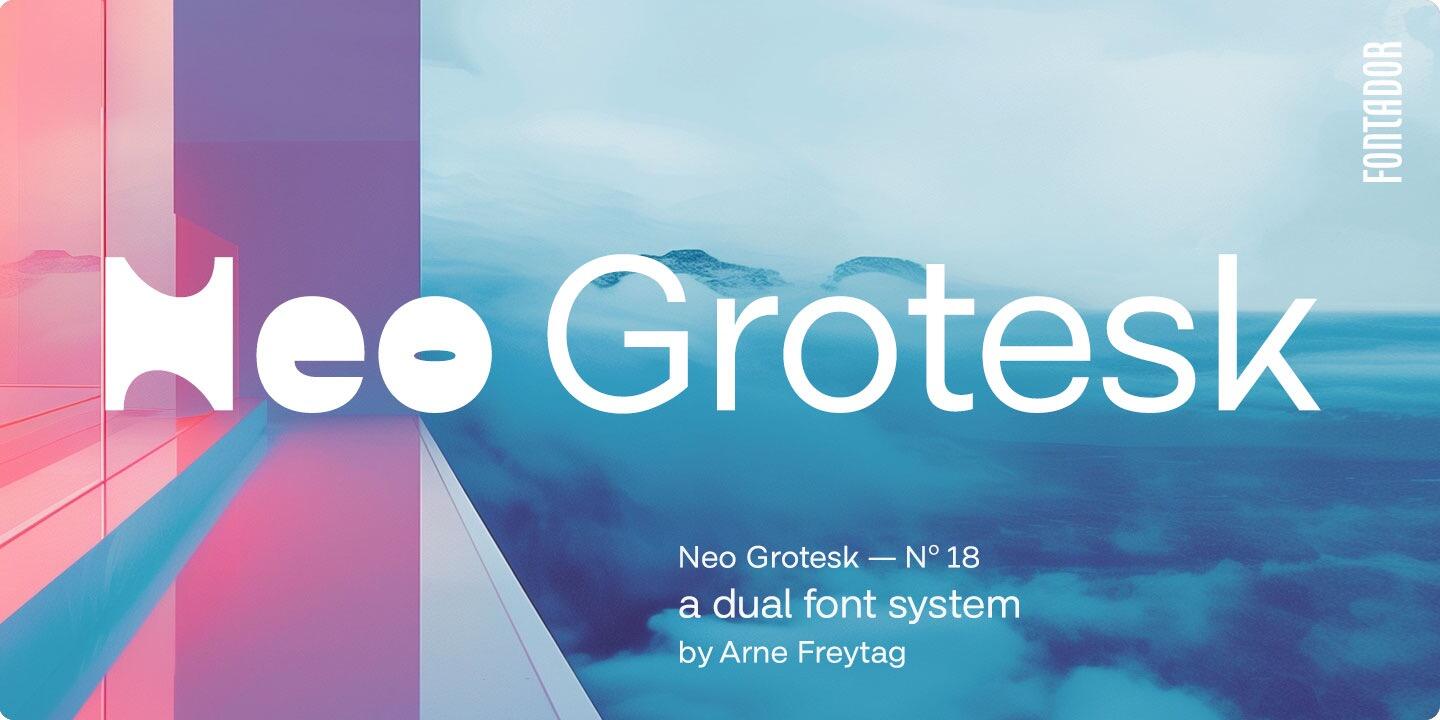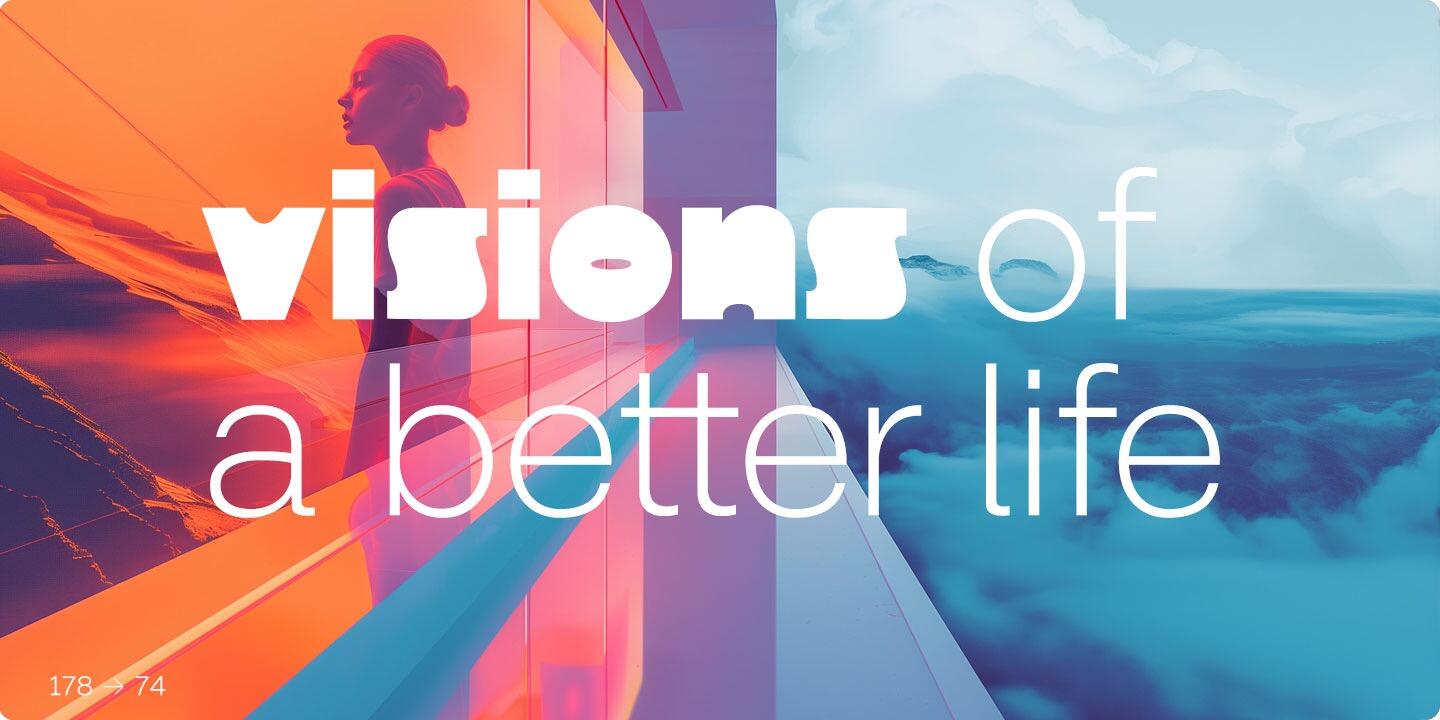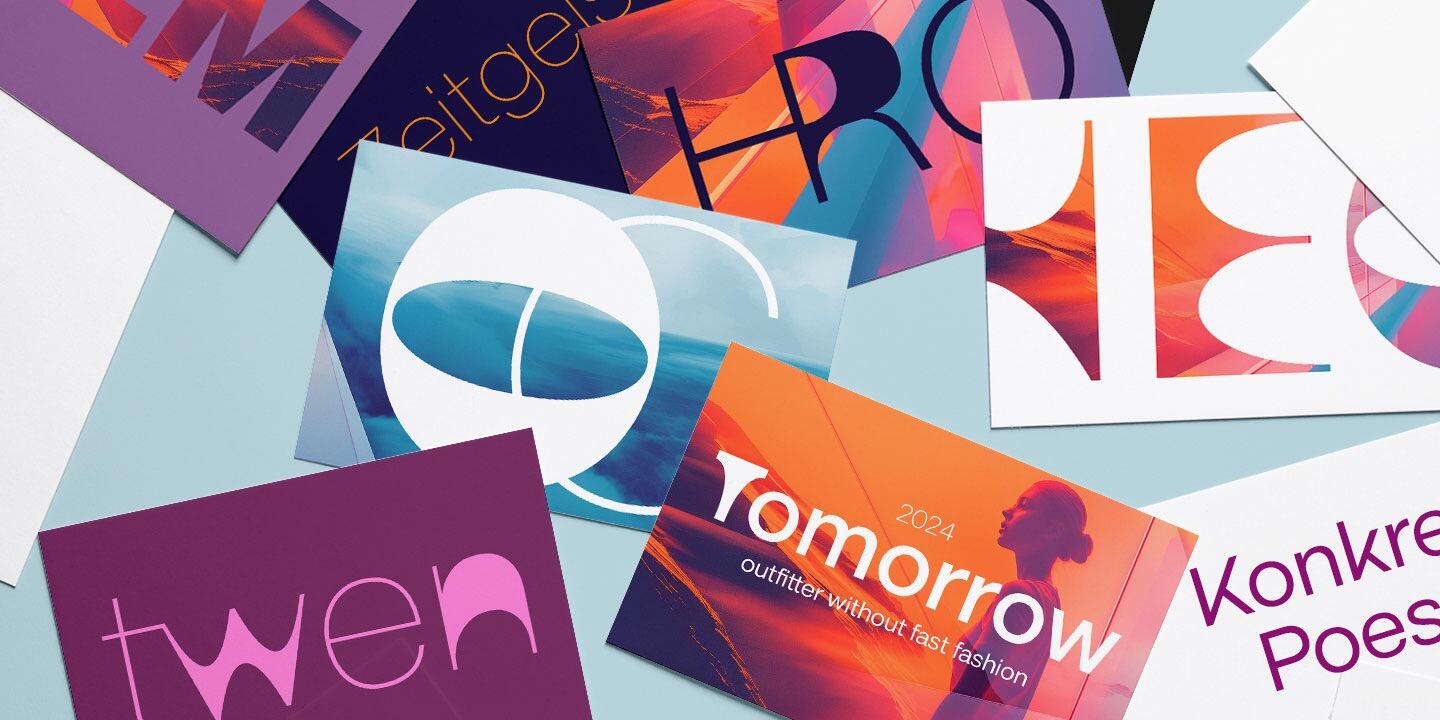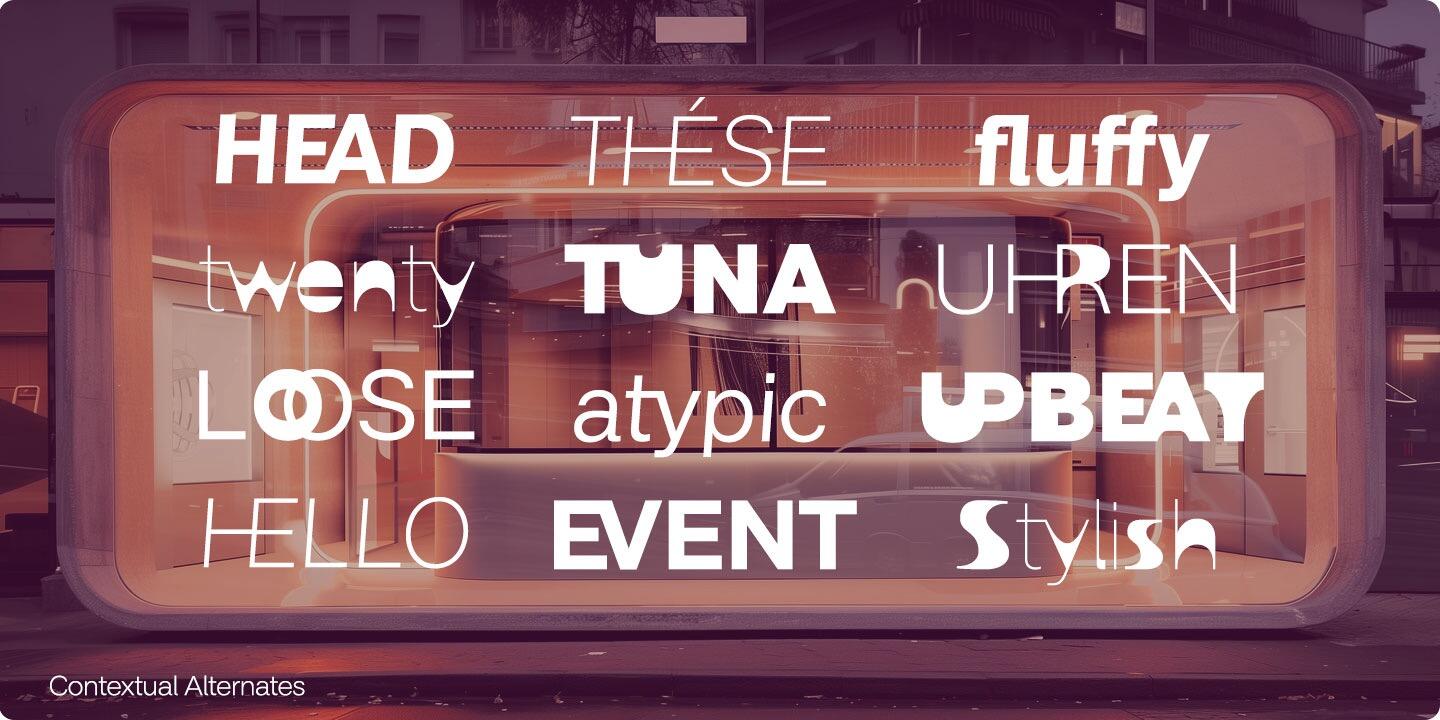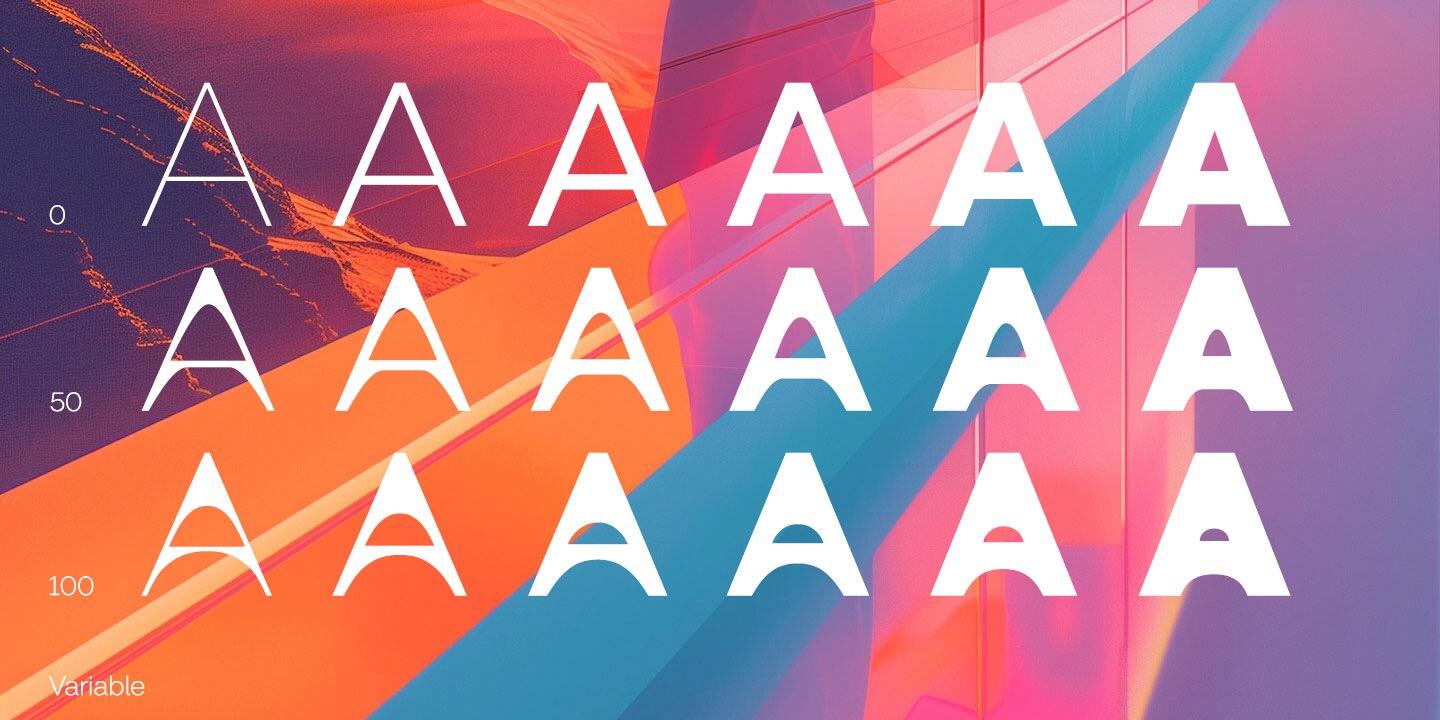
• Serifen:
• sans
• Antiqua geometrisch
• Versaleszett:
• enthalten
Die Neo Grotesk von Arne Freytag ist der Versuch eines dualen Schriftsystems in verschiedenen Strichstärken. Die Basis bildet eine moderne, sachlich geprägte Sans Serif im Stil einer Neuen Grotesk, während die zweite Schriftvariante auf der Grundform der ersten aufbaut und die Formen durch Rundungen variiert, ähnlich einem Weichzeichner-Effekt.
Neo Grotesk ist in zwei Versionen erhältlich: entweder klassisch als duale Schriftfamilie mit 18 unterschiedlichen Schnitten oder als variabler Font.